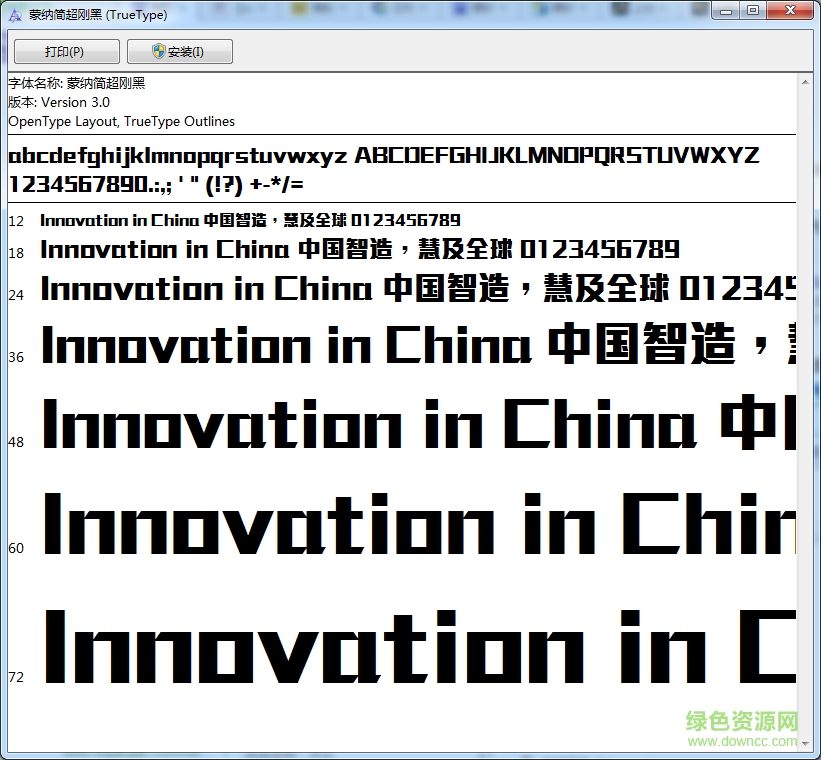
mstiffheiprc ultrabold字體即蒙納超剛黑PRC版是一款簡潔大方的電腦字體,適用于名片設(shè)計(jì)、圖文出版印刷、美工創(chuàng)作等領(lǐng)域,安裝就可使用非常便捷??靵砭G色資源網(wǎng)下載體驗(yàn)吧!
mstiffheiprc ultrabold是一款極具個(gè)性的字體,改字體非常硬氣大方,可以廣泛應(yīng)用于廣告設(shè)計(jì)、宣傳海報(bào)、ppt、影視制作以及任何使用文字的領(lǐng)域,有需要的朋友可以免費(fèi)下載收藏。